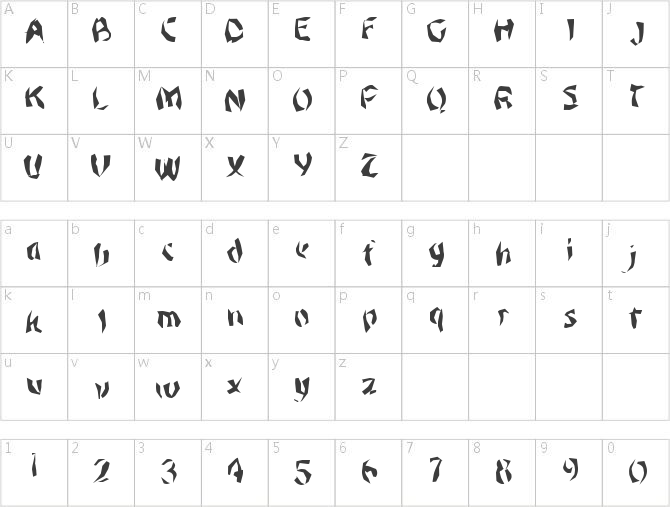
FZ WACKY 45 詳情頁(yè)
FZ WACKY 45字體字庫(kù)是一款讓人賞心悅目、百看不厭的英文字體,適合各類(lèi)廣告和產(chǎn)品包裝設(shè)計(jì)應(yīng)用,字體大小0.05MB,格式為ttf字體,上傳用戶(hù)是快霸中國(guó),作者/版權(quán)方為未知